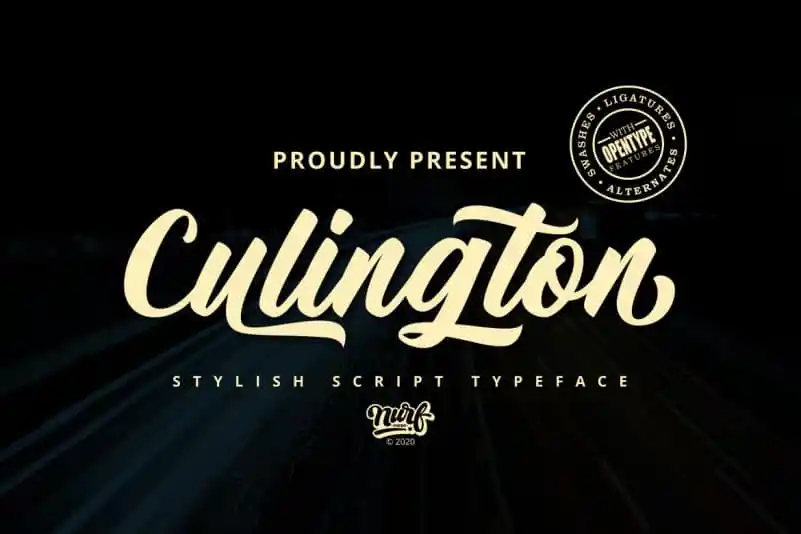
Culington Script Font – Download Grátis
A Culington Script Font é uma opção perfeita para quem busca uma fonte de escrita manuscrita que adorne seus projetos criativos. Esta fonte traz um toque artesanal e elegante, ideal para aplicações como logotipos, cartas personalizadas, embalagens de produto, letras em cabeçalhos ou até mesmo rótulos. Ela também suporta várias línguas e inclui alternativas e ligaturas no OpenType, tornando-a uma escolha versátil para múltiplas aplicações gráficas. Este é um recurso excelente para quem procura uma fonte de escrita manuscrita que possa se adaptar a diversos formatos e tamanhos em projetos do dia a dia e trabalhos profissionais. A Culington Script Font, criada pela incrível equipe da nurfdesigns, oferece tanto versatilidade quanto beleza para ilustrar seus ideais de design.